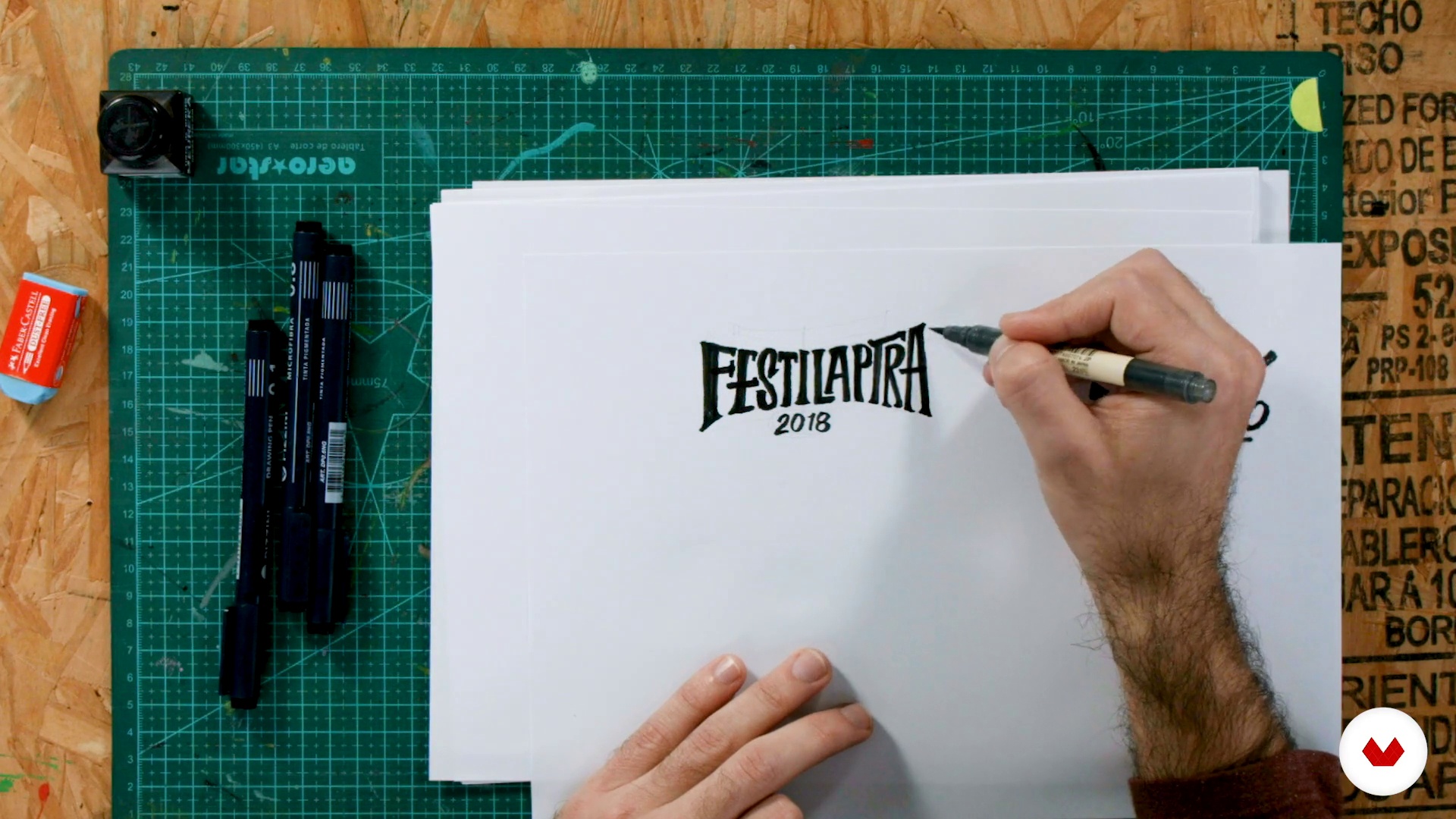
Conception d’une identité visuelle à partir de l’illustration
Typographie
À propos de la leçon : Typographie
“Dans cette leçon, nous allons jouer avec la typographie. Le texte en tant qu'image est beaucoup plus fort que l'image seule et c'est pourquoi il est intéressant de l'inclure dans l'étape d'illustration.”
Dans cette leçon, HolaBosque aborde le sujet : Typographie, qui fait partie du cours Domestika en ligne : Conception d’une identité visuelle à partir de l’illustration. Développez un univers de marque en utilisant des dessins dans vos travaux graphiques.
“Dans cette leçon, nous allons travailler avec la typographie. Notre idée avec le cours est de travailler avec des illustrations à la conception ultérieure. Nous voulons ajouter quelque chose en plus, quel est ce travail typographique, ce que nous utilisons quotidiennement dans notre travail. L'idée de pouvoir générer une marque ou une option de marque faite à la main pour plus tard, lors de la numérisation, avoir n'importe quelle option qui peut déjà être combinée avec une police numérique ou à utiliser uniquement cette marque faite à la main. Nous allons travailler le marquage aussi des ba...”